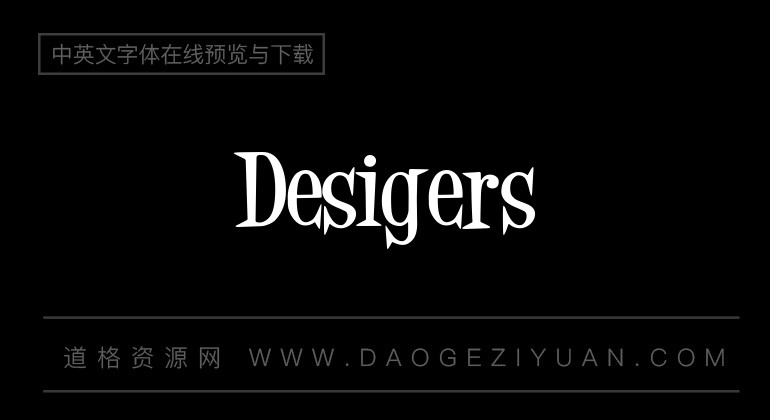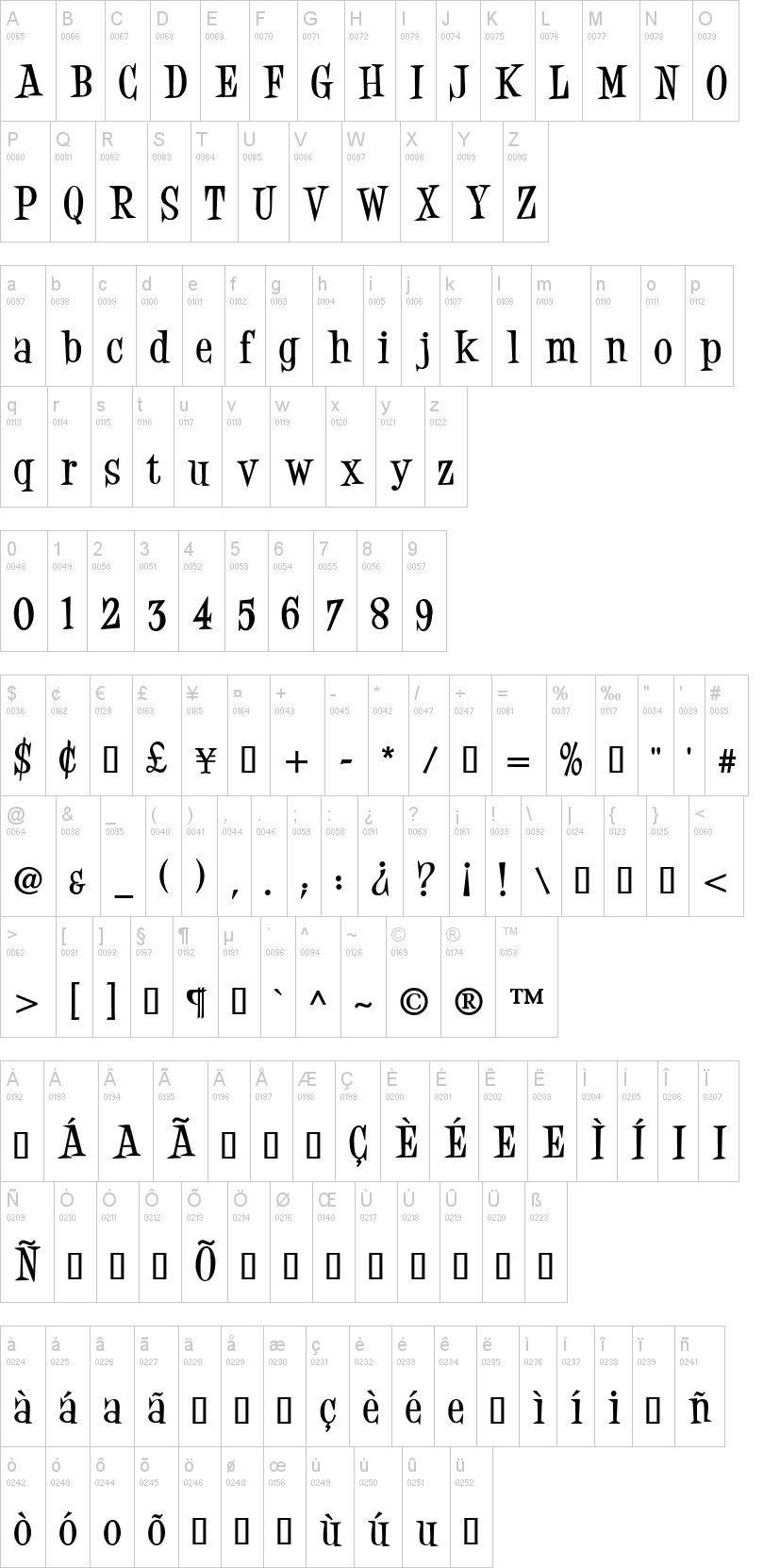
Desigers
Desigers 字体是一款专为设计师量身打造的字体,由英国设计师 Jack Harvatt 创作。它具有简洁、精致、易读的特点,可以满足设计师对字体的个性化需求。Desigers 字体具有多种字形,包括细体、粗体、斜体等,可以满足不同的设计需求。它有着优美的线条,即使在大尺寸下也能保持清晰度,使用起来十分方便。Desigers 字体还具有非常高的可视性,可以在多种设计中使用,是一款理想的设计字体。
Desigers是一款非常不错的手写艺术字体,具有很好的视觉感,适合于文化类的宣传设计、商业类品牌的广告和产品包装设计以及个性化文字排版等较多场景。
Desigers字符映射图